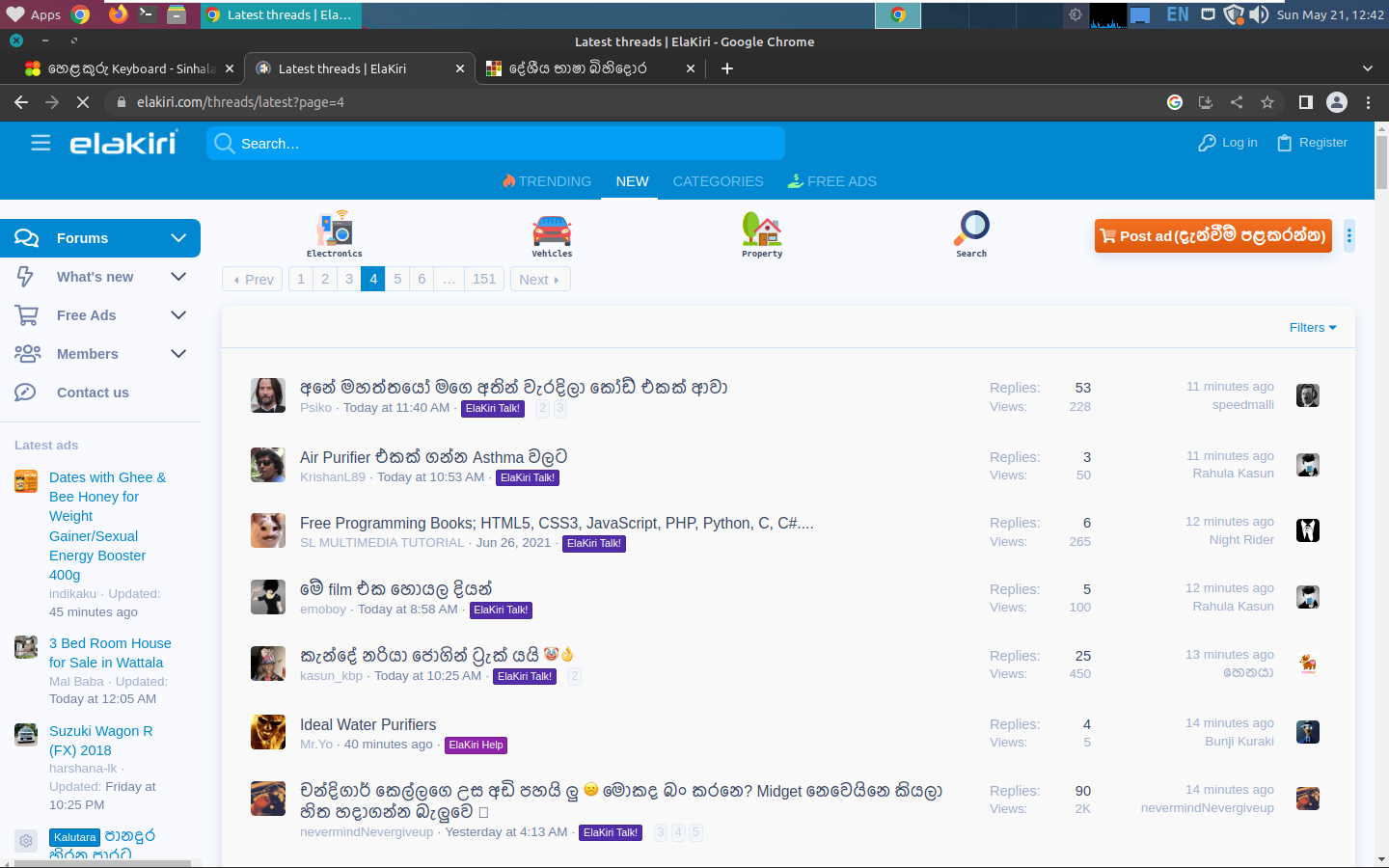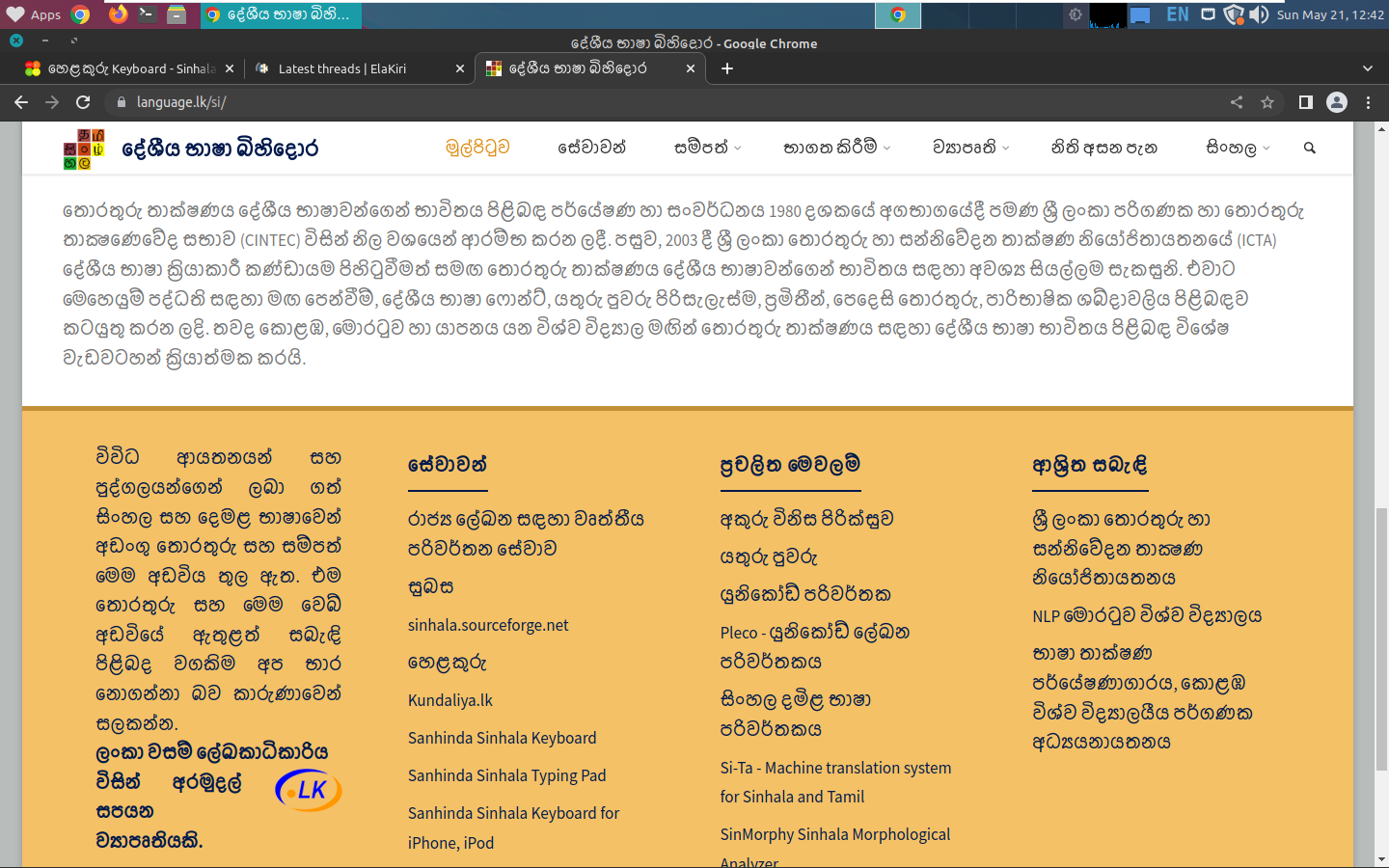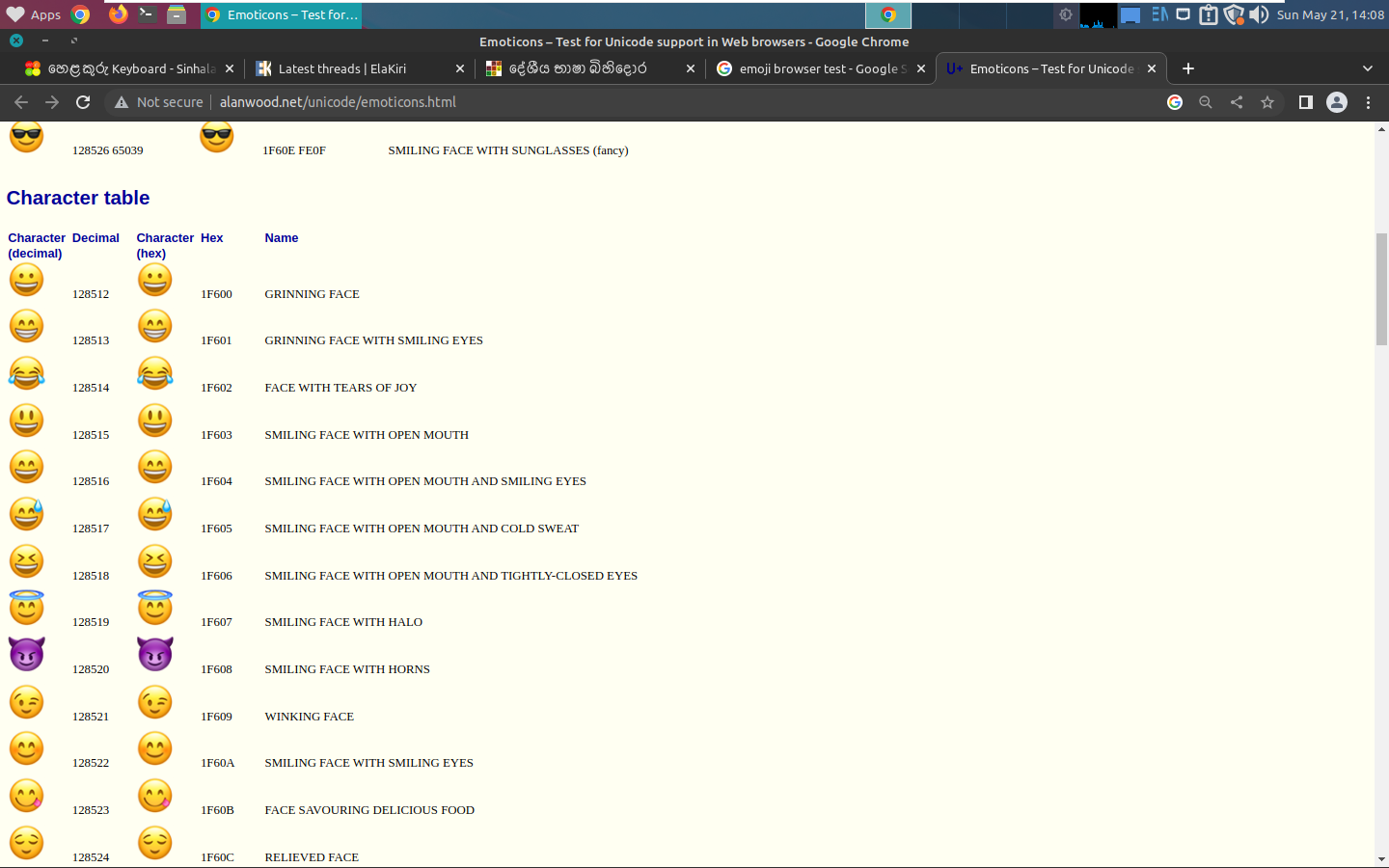
Linux වලට ලස්සන Apple🍎 සිංහල Font එක දාමු | Full guide For Beginners
ලගදි Linux වලට පොඩ්ඩක් බැහැල ඉගෙනගන්න කියල හැදුවා. ඒත් Browser එක open කරපුගමන් Default එන සින්හල Font එක දැක්කම වමනෙට වගේ ආව නිසා මුලින්ම ඒක මාරුකරන් හිටියනම් හොද‍යි කියල හිතුනා:yes:( මට පෞද්ගලිකව OS එක කොච්චර Powerful උනත් වැඩකෑලි තිබ්බත් වැඩක් නෑ එකත් UI එක පොඩ්ඩක් බබා වගේ තියෙන්න ඕන ලෙඩක් තියනව. නැත්නම් හිතට හරි නෑ වගේ:nerd:)
ඉතින් මම කාලයක්ම Hardcore Apple ෆෑන් කෙනෙක් නිසා සහ මම ඒ Font එකට Addicted නිසා ඇපල් සින්හල ෆොන්ට් එකම ලිනක්ස් වලටත් දාගන්න තීරණය කරා. කිරියෙත් මේකට ආස අය ඉන්නවනම් දාගන්න විදිහ steps විදිහට දානව කැමති අය වැඩක් ගන්ඩ:P
මම මේ ලියන්නෙ Linux Mint වලින් මම Setup කර ගත්ත විදිහ
යට තියෙන්නෙ ඇපල් සින්හල ෆොන්ට් එක ලිනක්ස් වල පේන විදිහ(හිතුවට වඩා ලස්සනයි)
PS: ඇපල්ම කියල නෑ ඕනම සිංහල ෆොන්ට් එකක් මේ විදිහට setup කරන්න පුලුවන්